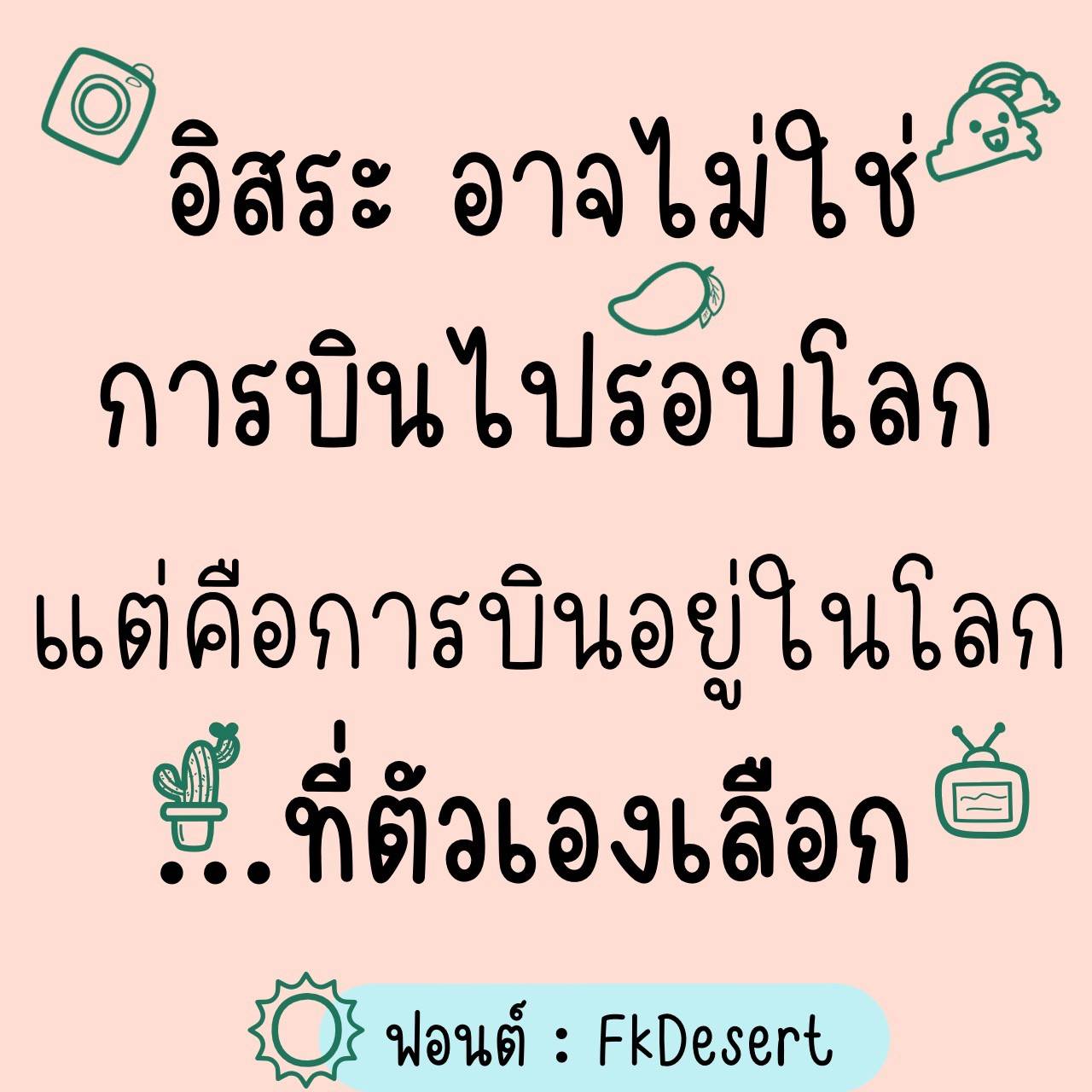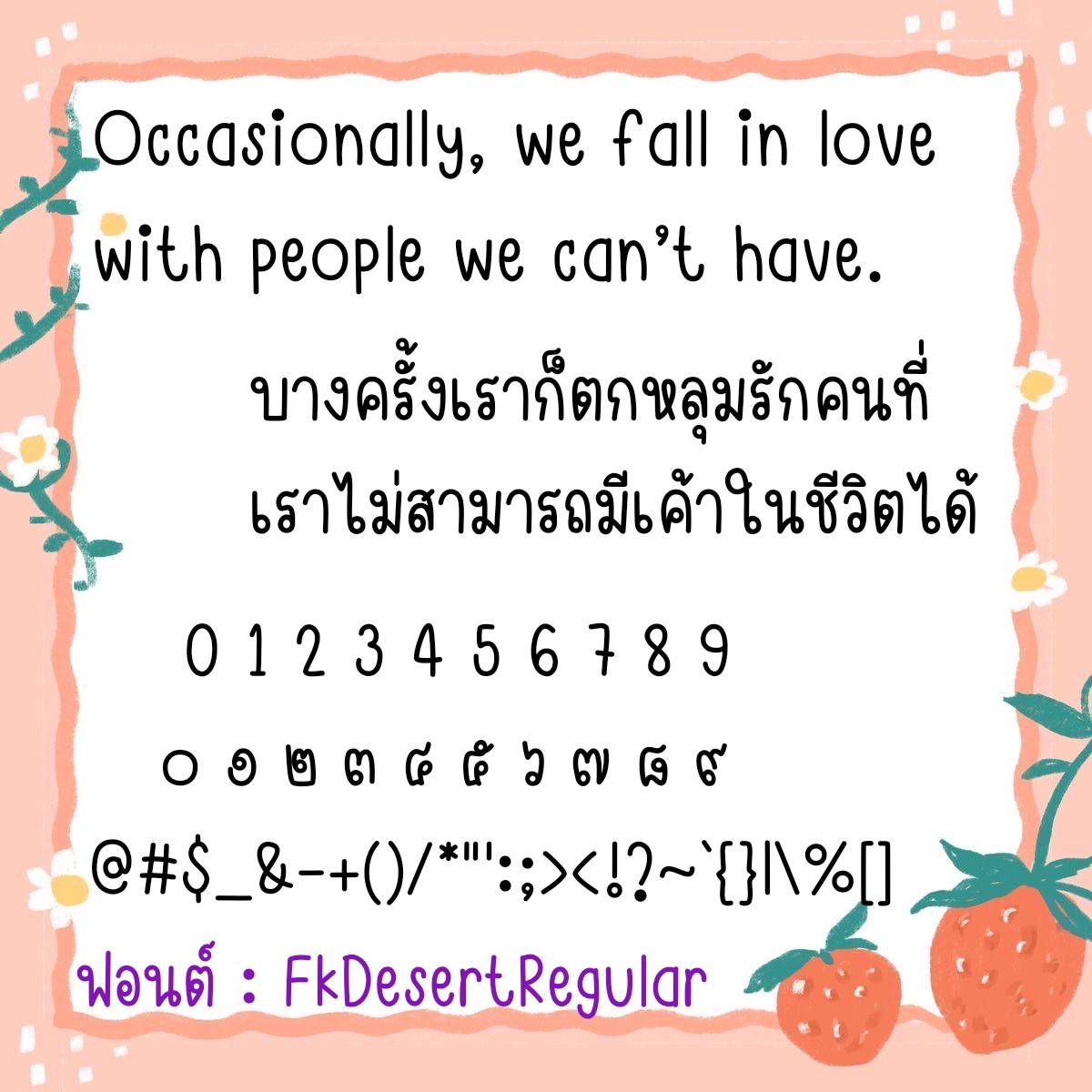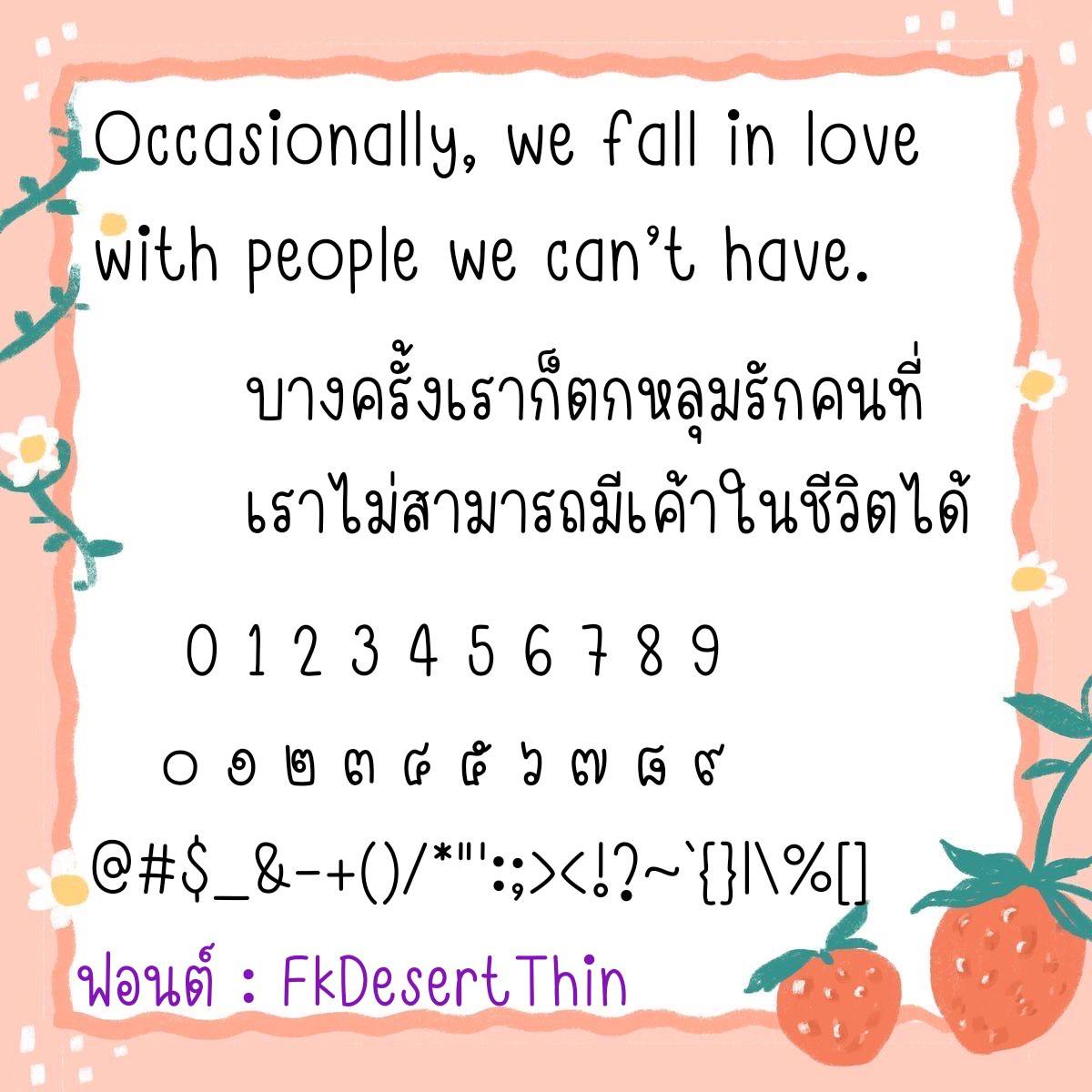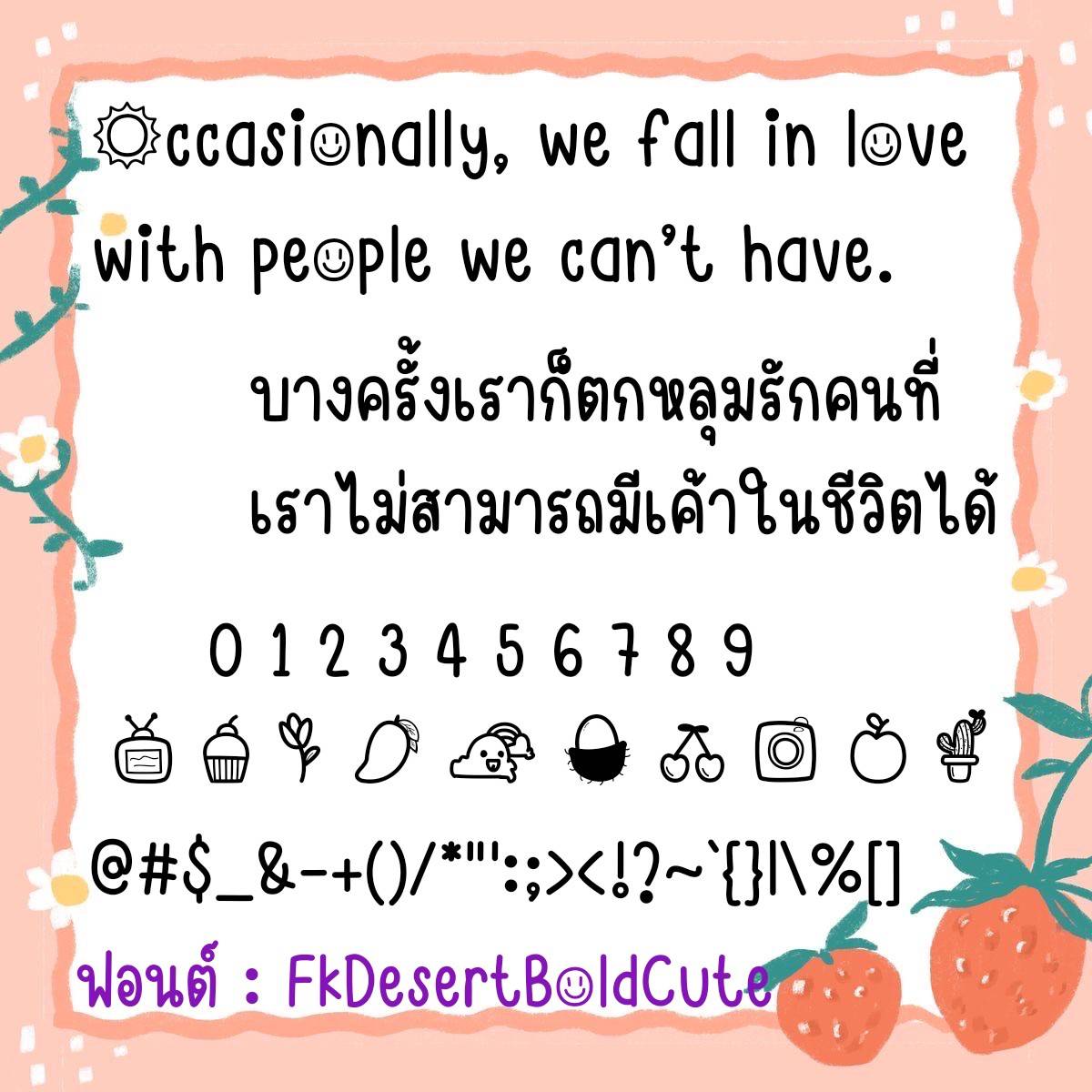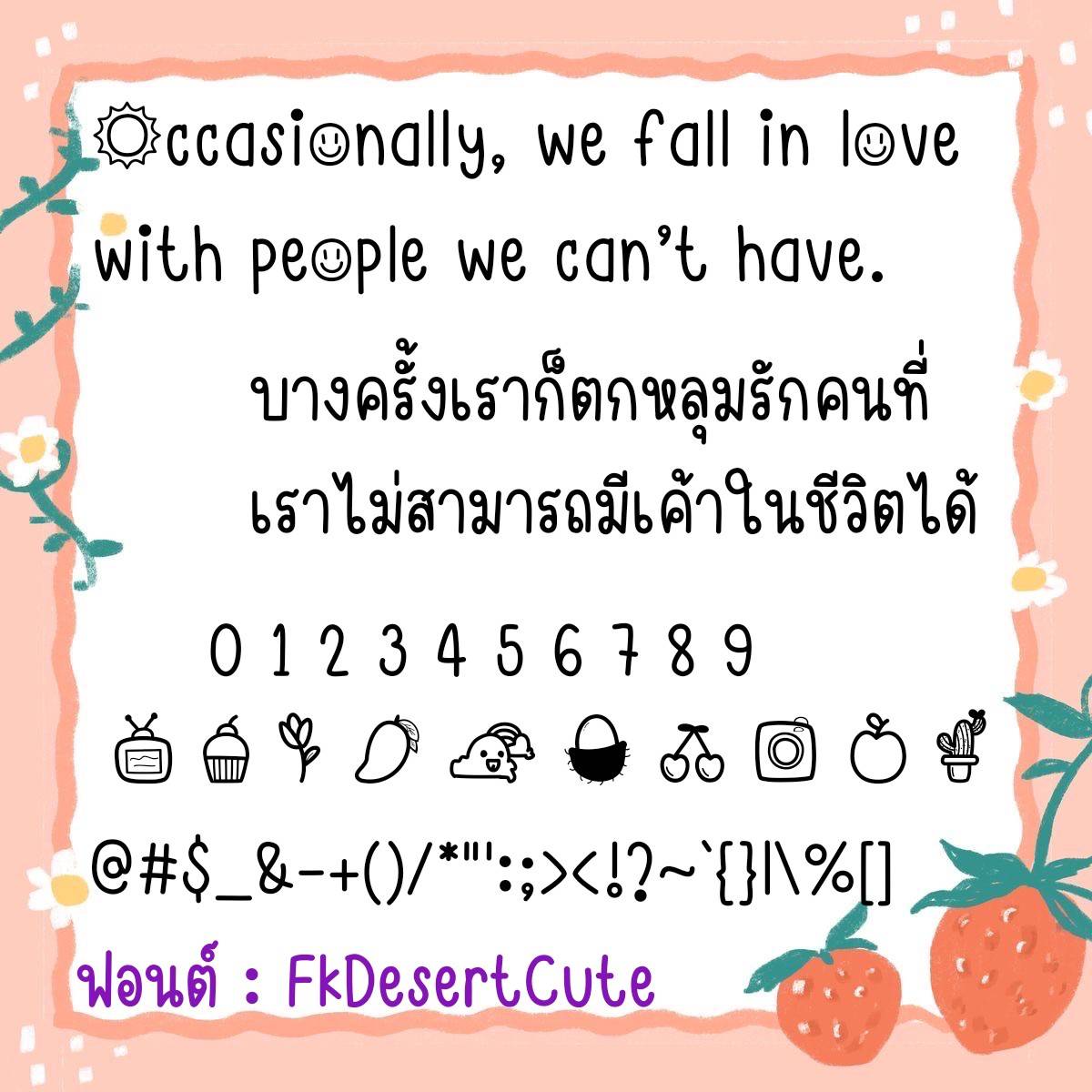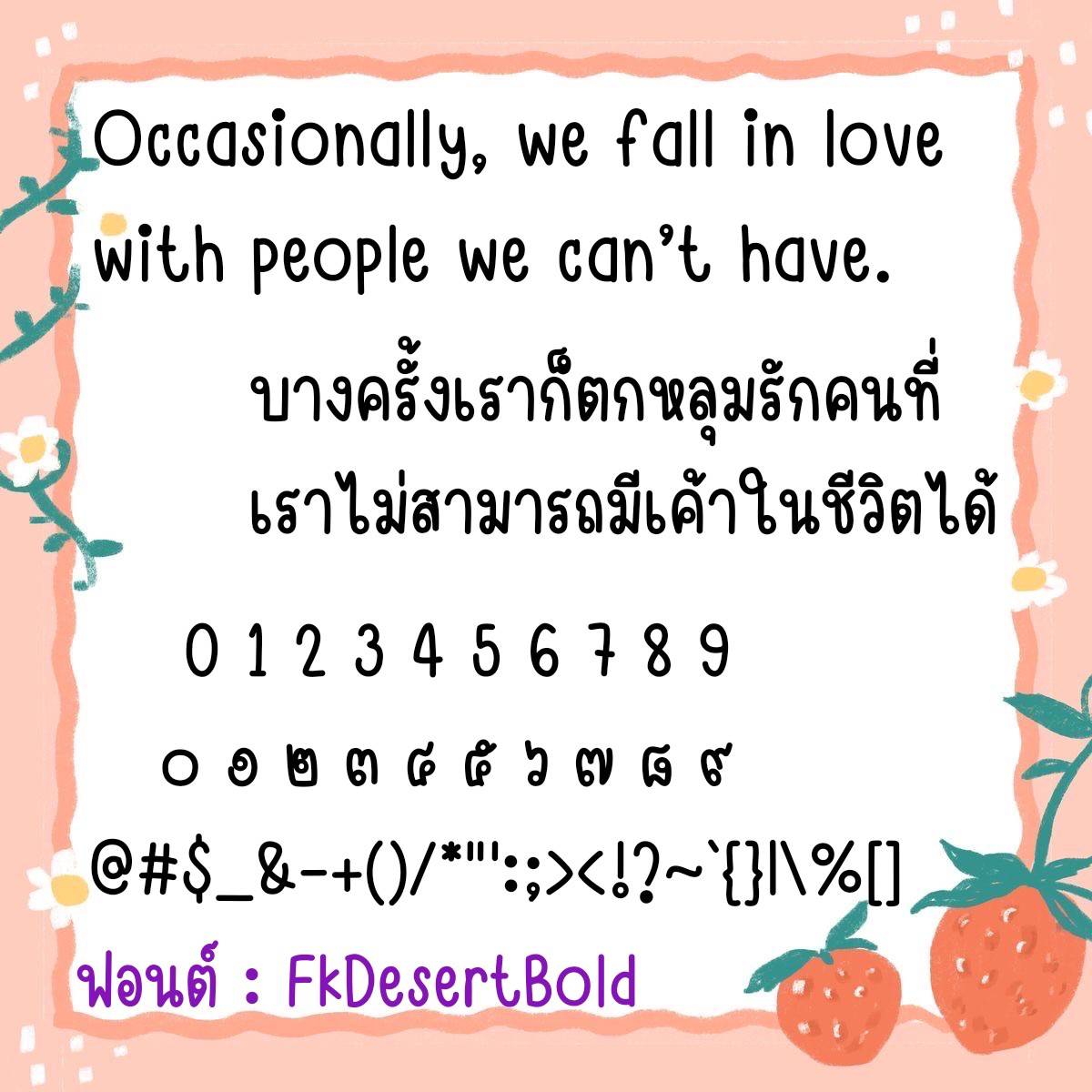
Font FkDesert
ชื่อสินค้า : Font FkDesert 💚
🔸 ฟอนต์ลายมือแนววัยรุ่น ฟอนต์มีความน่ารักดูสบายๆในตัว ใช้งานได้หลากหลาย ทำงาน,จดสรุป,ชีสเรียนได้หมด และยังมีไฟล์อิโมจิน่ารักๆ ที่ใช้แทนเลขไทยให้ด้วยค่ะ 🥰💙
🔹 A handwritten font for teenagers. The font is cute and easy on the eyes. It can be used for many purposes, such as working, taking notes, or studying. It also has a cute emoji file that can be used instead of Thai numerals. 🥰💙